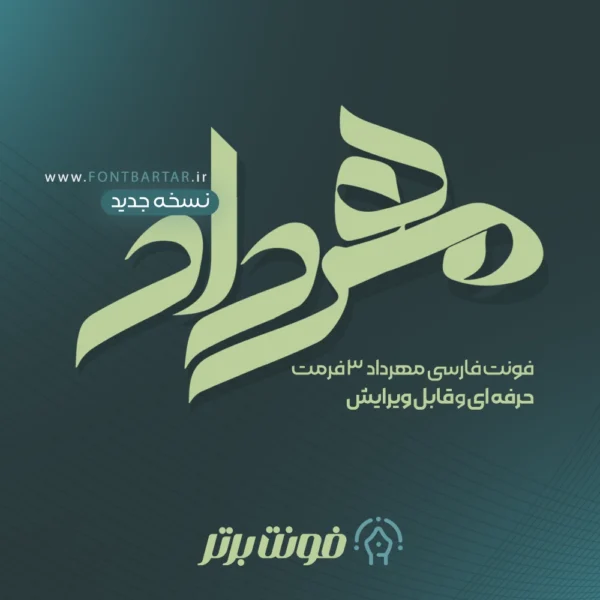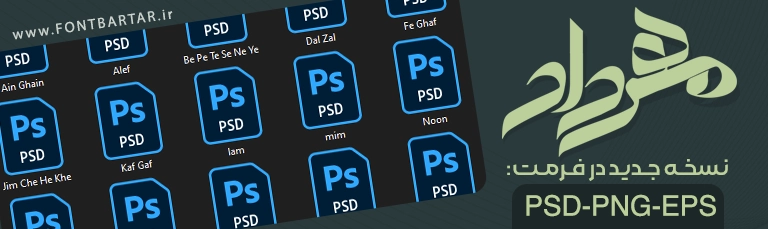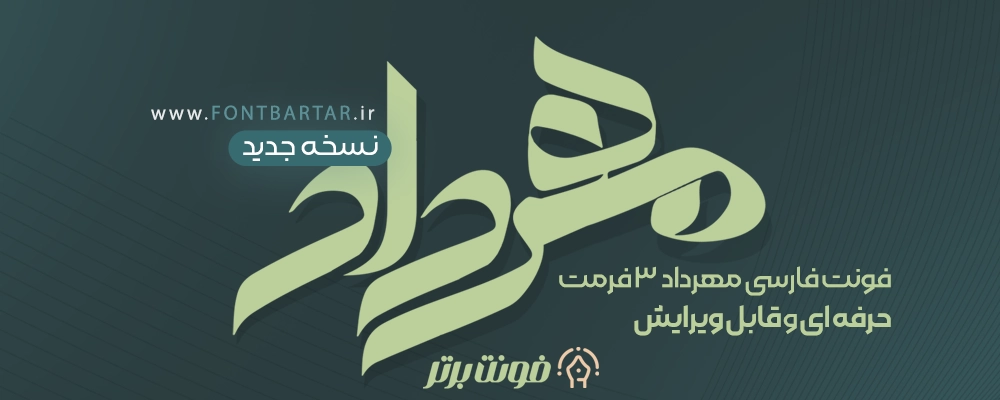
فونت جدید مهرداد
فونت فارسی مهرداد
Mehrdad Font
فونت فارسی مهرداد
فونت لوگوتایپ و فونت تایپوگرافی مهرداد
فونت مهرداد یکی دیگر از فونت های طراحی لوگوتایپ و تایپوگرافی می باشد، دانلود فونت لوگوتایپ مهرداد با طراحی حرفه ای و انعطاف پذیر می باشد و این امکان را فراهم می آورد که به راحتی بتوانید حروف را در کنار هم قرار دهید، با خرید فونت فارسی مهرداد می توانید بدون هیچگونه دانشی لوگو تایپ طراحی کرده و تایپوگرافی های زیبایی انجام دهید و از آن کسب درآمد کنید.
دانلود فونت لوگو مهرداد بر خلاف سایر فونت ها به صورت لایه باز بوده (psd) و امکان تایپ مستقیم در نرم افزار ها را ندارد همچنین شامل تمامی حروف از الف تا ی می شود این فونت به چینش های مختلف می تواند در کمترین زمان این امکان را به طراح بدهد که یک لوگو تایپ حرفه ای برای کسب و کار های مختلف طراحی کند ویژگی های این فونت حرفه ای را باهم مرور کنیم.
📌مزایای استفاده از فونت زیبا مهرداد:
• لوگوتایپ فارسی تمامی حروف به صورت لایه باز
• ویرایش آسان حروف
• طراحی لوگوتایپ
• طراحی لوگو به صورت آسان و بدون هیچگونه آموزش
• فونت زیبا مهرداد شامل تمامی حروف از الف تا ی در تمامی حالت ها
📌دانلود فونت لوگوتایپ مناسب برای:
• دانلود فونت لوگو فارسی مهرداد مناسب عناوین و تیتر ها
• فونت مناسب کاور اینستاگرام و یوتیوب
• فونت لوگو بهترین گزینه برای تایپوگرافی پوستر ها
• گزینه مناسب برای طراحی لوگوتایپ سنگین